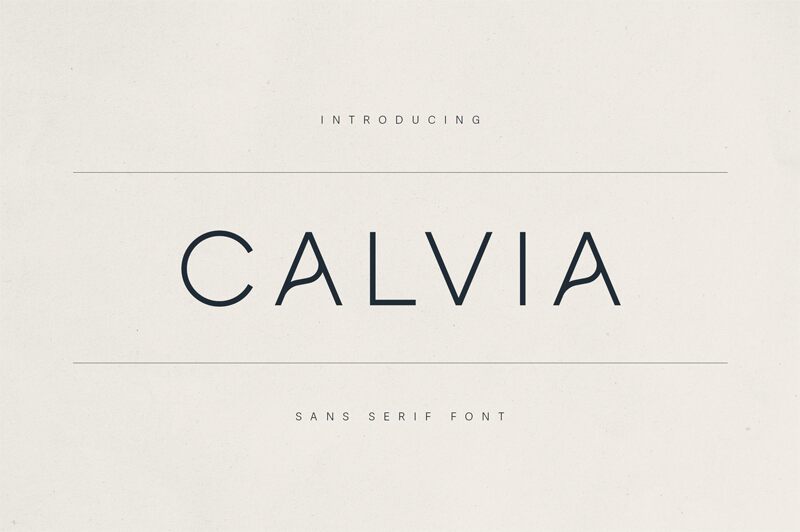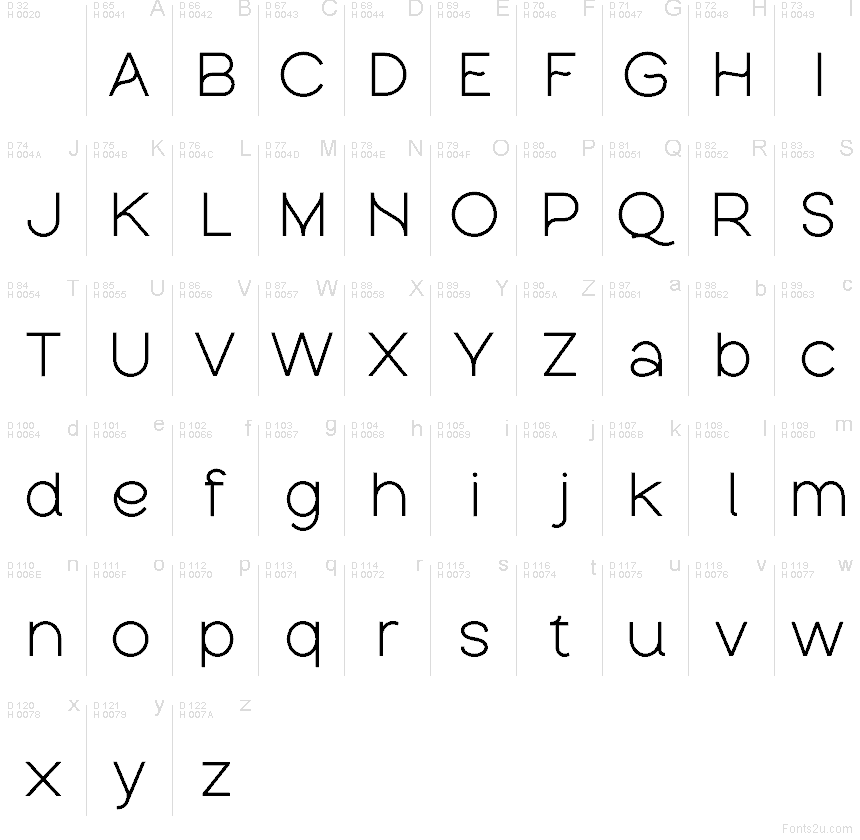
Calvia Demo Regular
Calvia je bezplatné geometrické bezpätkové písmo, ktorému dominujú široké kruhové krivky a veľmi striedme zvislé ťahy. Táto kombinácia dodáva písmenám otvorený, vzdušný rytmus, zatiaľ čo jednoduché tvary a rovnomerná hrúbka ťahov udržiavajú čistý vzhľad, ktorý nepôsobí mechanicky.
Jeho pokojná štruktúra skvele funguje v brandingu, na obaloch, plagátoch, v titulkoch aj v hlavičkách webov všade tam, kde chcete jemný geometrický prejav bez zbytočného vizuálneho šumu. Najviac vynikne pri krátkych názvoch a sloganoch, pretože široké okrúhle tvary a jednoduché spoje dodávajú aj niekoľkým slovám dostatočnú silu, aby orámovali layout bez toho, aby zahltili zvyšok stránky.